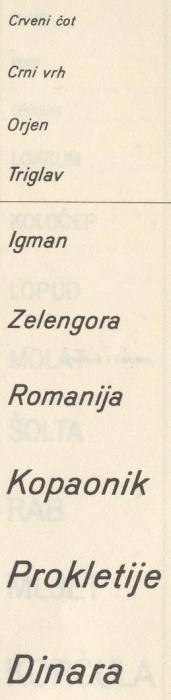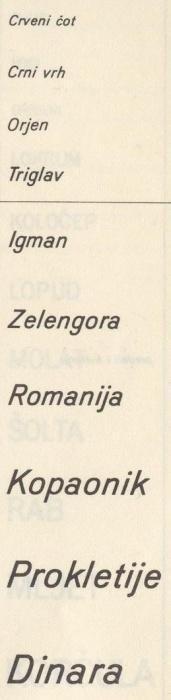
Schrift von alten topographischen Karten gesucht
ich suche nach der Schrift, die auf alten topographischen karten verwendet wurde (ex-Jugoslawien), und hoffe, dass jemand mir helfen kann.
Bei Berthold liefen diese Schriften früher unter der Bezeichnung »Planschrift« oder »Balken«. Ähnliche Schriften habe ich auch auf topographische Karten aus der Schweiz gesehen. Es kann aber sein, dass Du da etwas gefunden hast was mich besonders interessiert … sind diese Karten vielleicht bei Perthes in Gotha hergestellt?
Vielen Dank für die Antwort, der Hersteller war/ist aber das Geografische Institut aus Belgrad